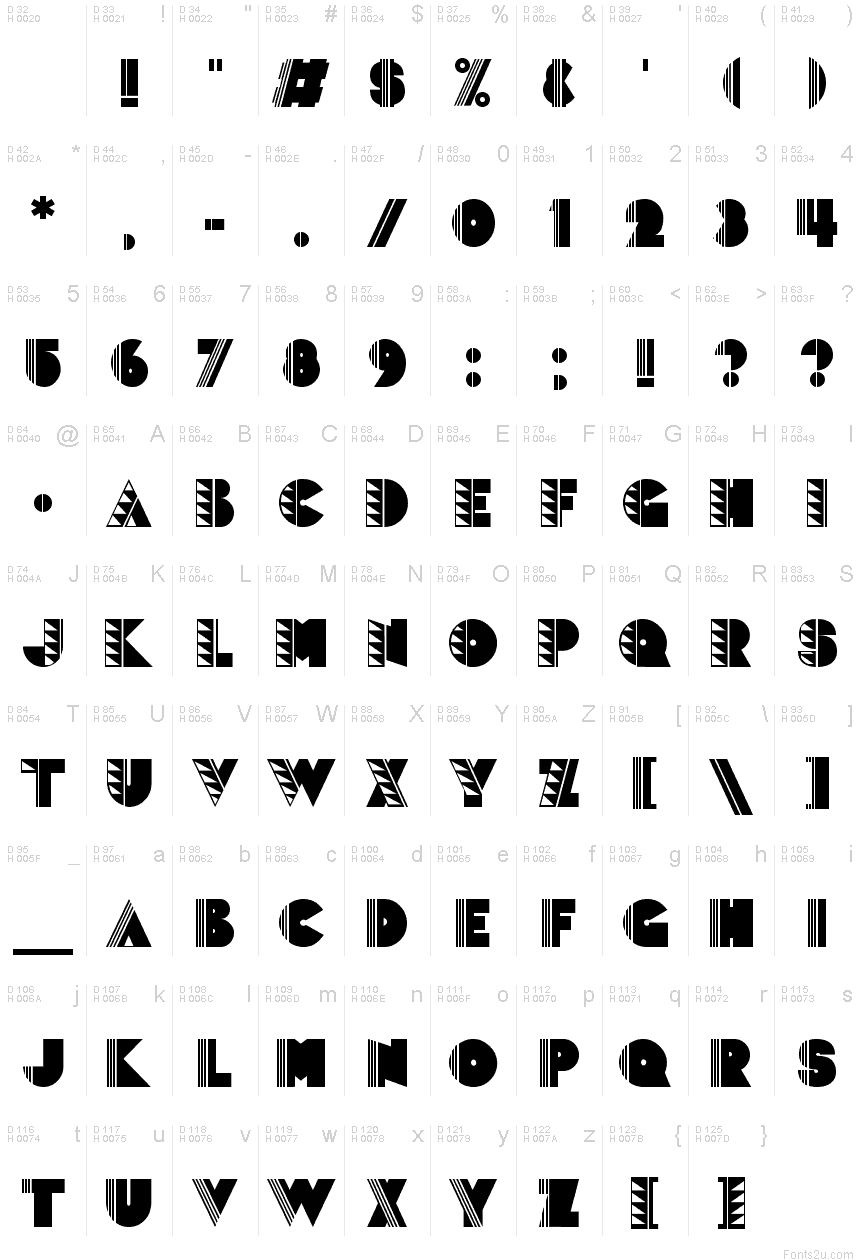
Poptics Two von Patricia Lillie ist eine kostenlose, groovige Display-Schrift mit dem pulsierenden Vibe der Op-Art. Die Buchstaben setzen sich aus massiven schwarzen Formen zusammen, die durch enge vertikale Streifen, kreisförmige Aussparungen und keilartige Einkerbungen unterbrochen werden – das sorgt für einen grafischen, plakativ-poppigen Stil, der direkt an die 70er Jahre erinnert.
Sie passt perfekt auf Plattencover, Event-Poster, Boutique-Verpackungen, Magazin-Titelzeilen und Title Cards – überall dort, wo ein kostenloser Font die gesamte Stimmung allein tragen muss. Da die Zeichen fast so sehr wie Musterblöcke wirken wie wie Schrift, kommt sie besonders bei kurzen Überschriften, Logo-Schriftzügen und Monogrammen zur Geltung, die einen popkulturellen Beat statt eines neutralen Tons suchen.